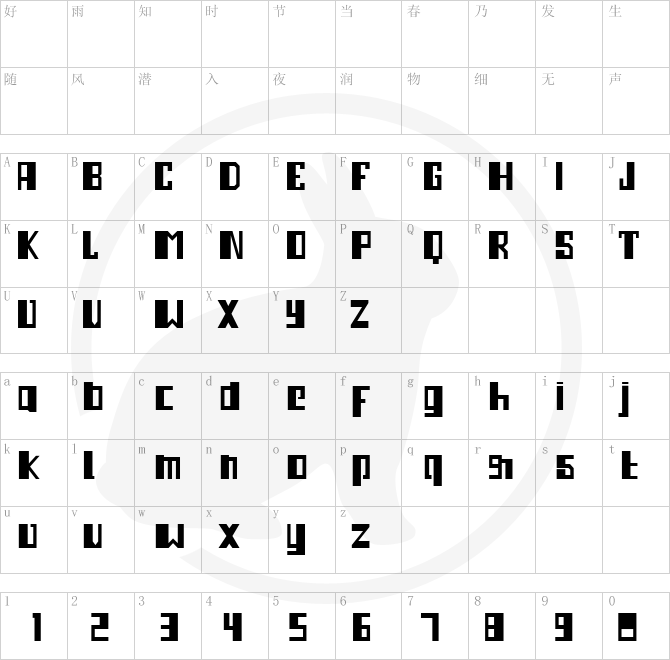
3M Ampleset.otf字体下载,这款字体结构工整、笔画清晰,兼顾美观与易读性,适用于标题、正文、海报、包装、LOGO 等多种场景。字形优雅稳定,风格百搭耐看,适配日常排版与创意设计,让文字呈现更舒适、更具质感。3M Ampleset.otf字体下载一笔一画,皆是细节,以均衡的比例、流畅的线条打造舒适视觉体验,字形端正大气,风格简约现代。无论是商业设计、品牌宣传还是日常排版,都能轻松驾驭,让文字更有格调与力量。3M Ampleset.otf字体下载字体下载。